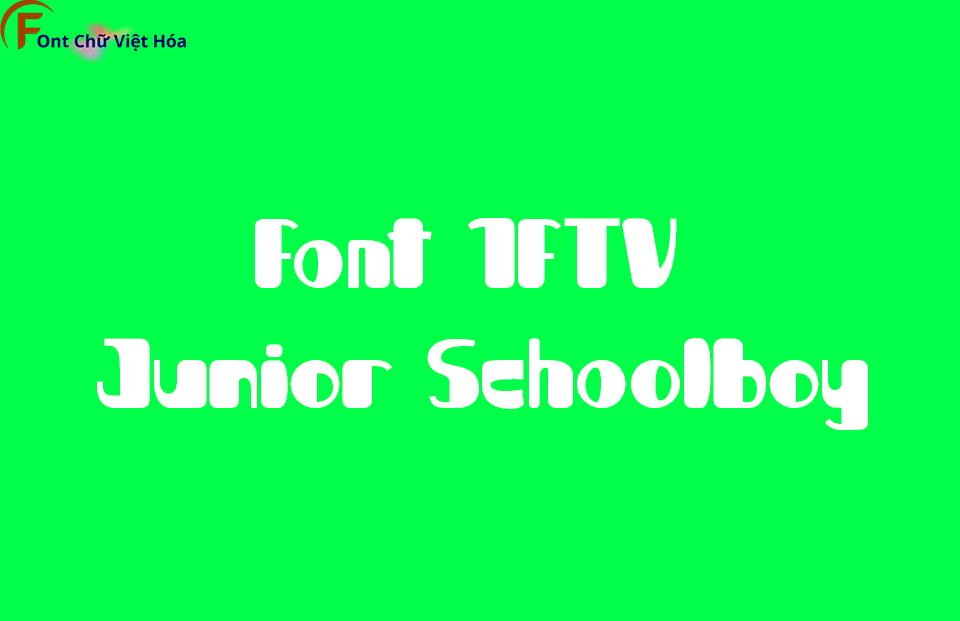
Font 1FTV Junior Schoolboy
Tác giả: PutraCetol Studio
Phân loại: Vui nhộn
Kiểu chữ: Display
Font 1FTV Junior Schoolboy là một kiểu chữ thuộc bộ Font 1FTV, được thiết kế dành riêng cho trẻ em và học sinh, với các nét chữ dễ đọc, thân thiện và vui nhộn. Kiểu font này thường được sử dụng trong các tài liệu giáo dục, bảng viết tay, hoặc những dự án sáng tạo dành cho lứa tuổi thiếu nhi. Với các đường nét mềm mại, dễ nhận biết, Font 1FTV Junior Schoolboy không chỉ giúp trẻ dễ dàng tiếp cận ngôn ngữ viết mà còn khuyến khích sự hứng thú trong học tập và sáng tạo.